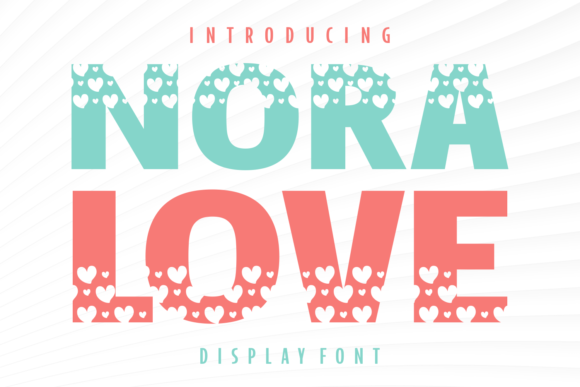
Nora Love Font
Nora Love Font – لمسة أنيقة لعشاق التصميم
أضف لمسة من الرومانسية والأناقة إلى تصاميمك مع Nora Love Font، الخط المثالي للمبدعين الذين يبحثون عن طابع أنثوي ناعم وفريد. يتميز هذا الخط بتصميمه الانسيابي وحروفه المتناغمة التي تضفي لمسة فنية على أي مشروع.
مميزات الخط:
✅ تصميم أنيق وانسيابي
✅ مثالي للدعوات، الشعارات، التصاميم الرقمية والمطبوعة
اجعل تصاميمك تنبض بالحب والجمال مع Nora Love Font! ????